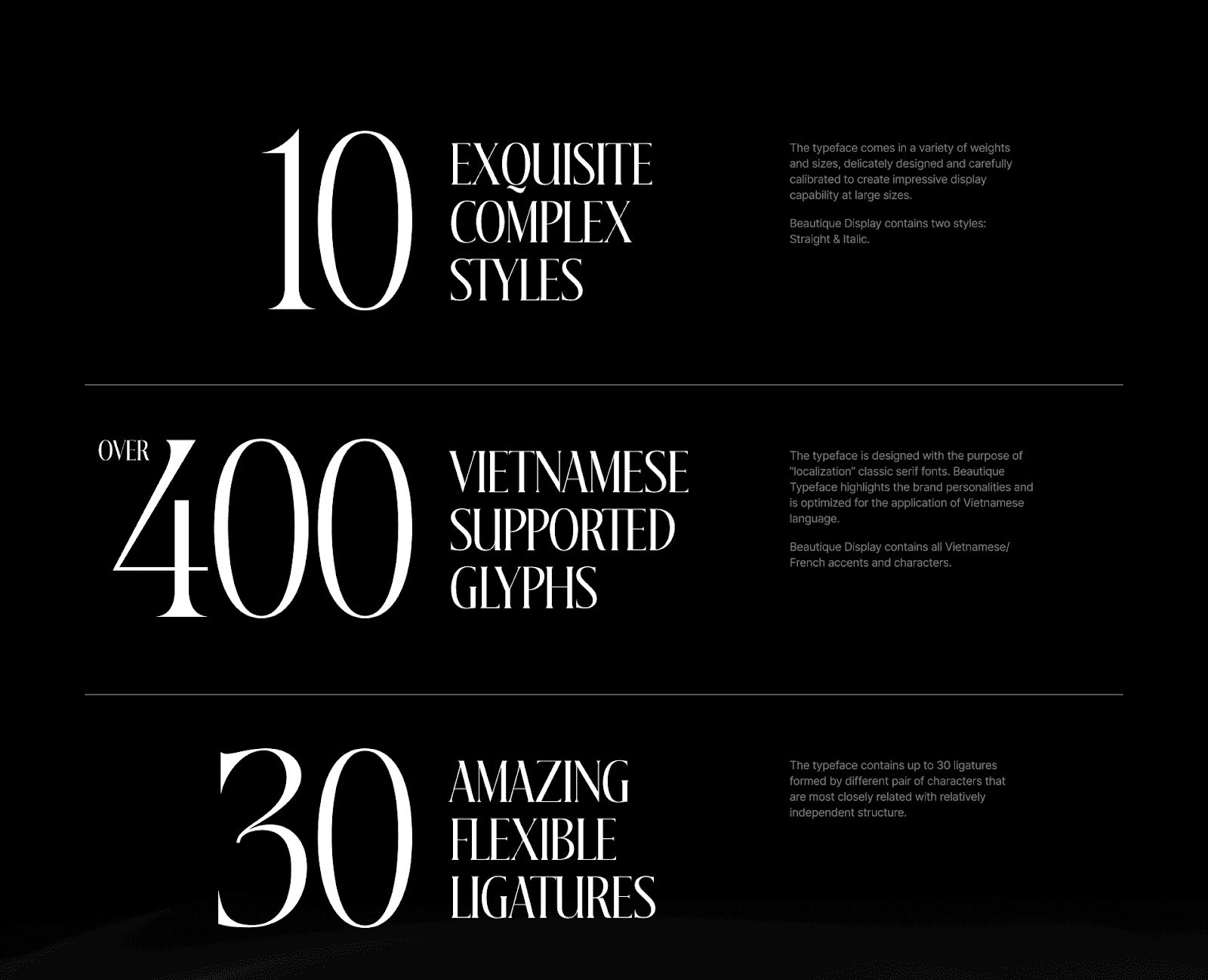
Font tiếng Việt Beautique Display cực đẹp (20 font)
Beautique Display Typeface được phát triển bởi Beautique, đây là bộ font chữ vô cùng chất lượng được thiết kế mang phong cách hiện đại bao gồm 10 font và 10 font condensed, font được thiết kế một cách tỉ mỉ với các đường nét độc đáo vì vậy bạn có thể sử dụng bộ font này cho nhiều thiết kế khác nhau như tạp chí, bìa sách, tiêu đề, quảng cáo, xây dựng thương hiệu...